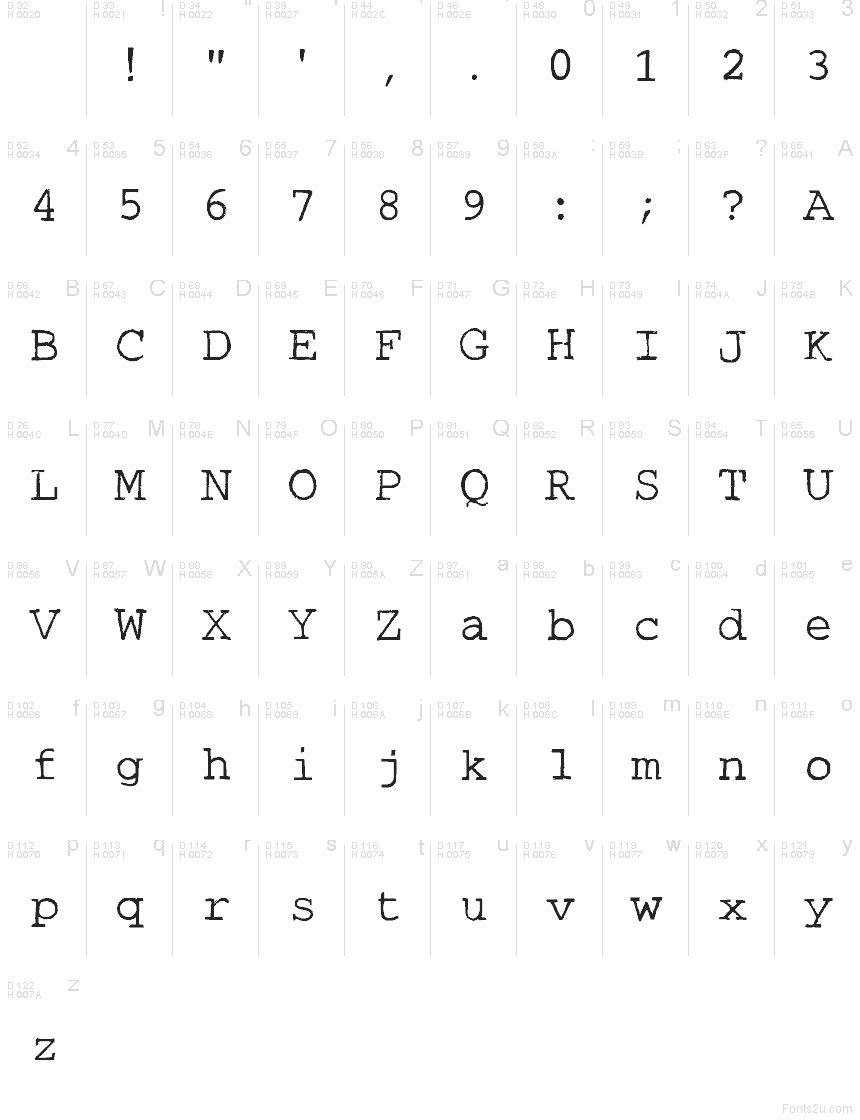
Jitter Creeps Regular
Písmo Jitter Creeps od Jitter Creeps je bezplatný font typu display s erodovaným vzhľadom, drsnými, poškriabanými okrajmi a nepravidelnými zárezmi v jednotlivých ťahoch. Jeho ručne kreslené tvary pôsobia ľahko nepravidelne a uvoľnený rytmus dodáva nadpisom a krátkym slovám obnosený, strašidelný charakter, bez toho, aby stratilo na čitateľnosti.
Jitter Creeps skvele funguje na hororových plagátoch, halloweenskych letákoch, štítkoch pre tematické akcie, obálkach kníh či fanúšikovskom tovare, pretože jeho patinovaný povrch prenáša túto neklidnú atmosféru aj v menšom množstve textu. Tento bezplatný font sa hodí aj pre akcenty v logách, detaily obalov a dekoratívne nadpisy, keď hľadáte skôr roztrhaný, strašidelný vzhľad ako z knihy príbehov než uhladené, bežné písmo.